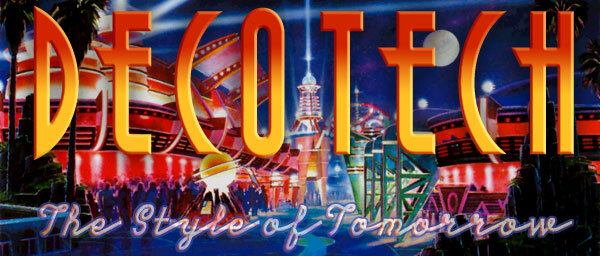
DecoTech TL
DecoTech TL è un font display retro gratuito che canalizza il puro glamour dell'Art Déco con un tocco moderno e slanciato. Lettere alte e condensate, verticali decise e curve geometriche eleganti richiamano le atmosfere delle insegne dei vecchi cinema e dei grandi hotel. Il ritmo incalzante e la spaziatura stretta della famiglia DecoTech creano un wordmark d'impatto, pronto per i poster, che risulta allo stesso tempo nostalgico e taglientemente moderno.
Grazie a DecoTech TL, questo font gratuito brilla su poster di eventi, branding di lusso, packaging, copertine di libri, segnaletica e loghi d'impatto. Le sue forme scultoree rendono al meglio nei grandi formati, dove le silhouette drammatiche possono davvero respirare; aggiungi un carattere sans serif pulito e discreto per il testo di supporto e avrai un sistema completo di ispirazione vintage.